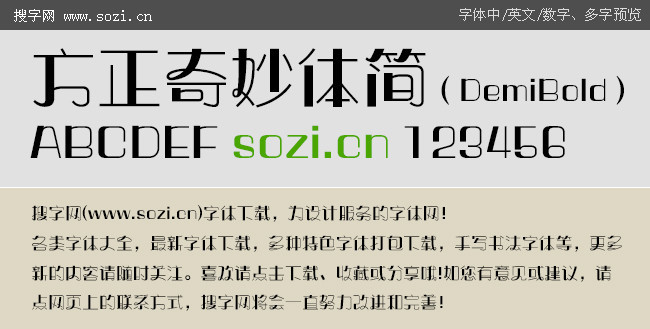
方正奇妙體簡(jiǎn)DemiBold
搜字網(wǎng)提供一款方正奇妙體簡(jiǎn)中文字體下載,方正奇妙體風(fēng)格獨(dú)特,時(shí)尚高雅,品味出眾,筆劃都以橫細(xì)直粗,增強(qiáng)了美感,充滿(mǎn)個(gè)性的字體太誘惑了。共有8種粗細(xì),商業(yè)用途廣泛,男女老少都合適,如手機(jī)字體,動(dòng)畫(huà),化妝品,女士飾物、時(shí)裝、酒店、飲料廣告宣傳和包裝設(shè)計(jì)等!
• 風(fēng)格類(lèi)別: 海報(bào)POP體